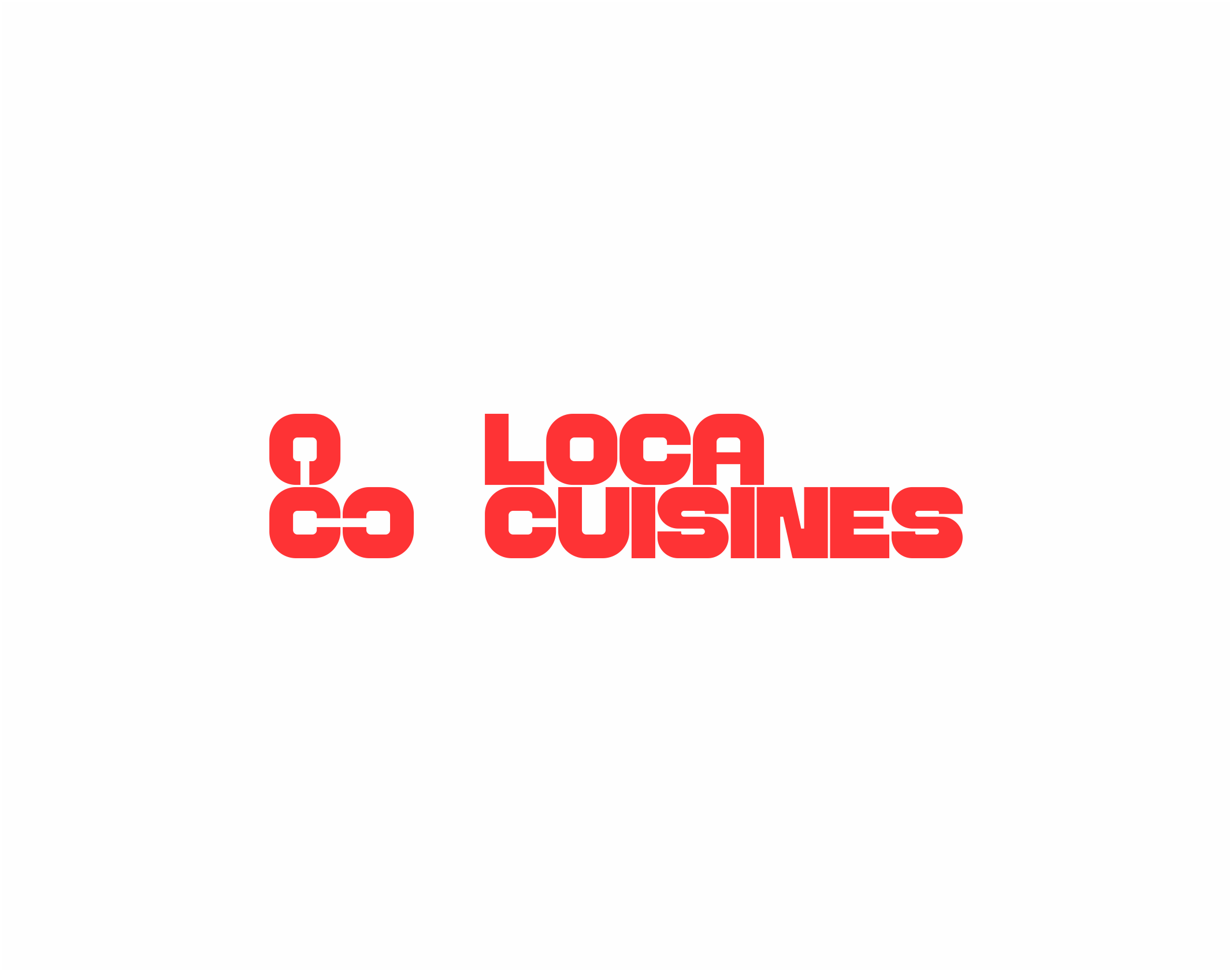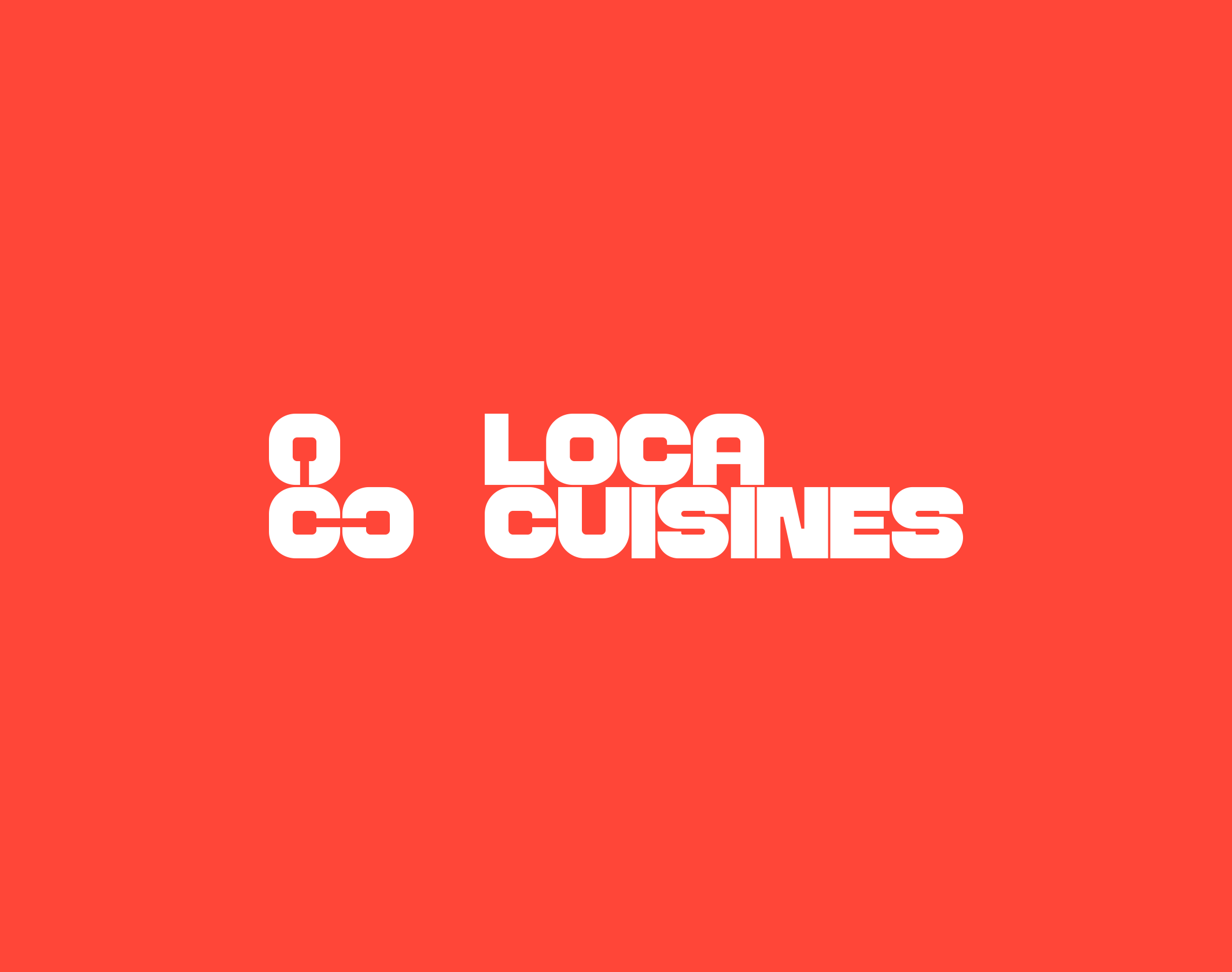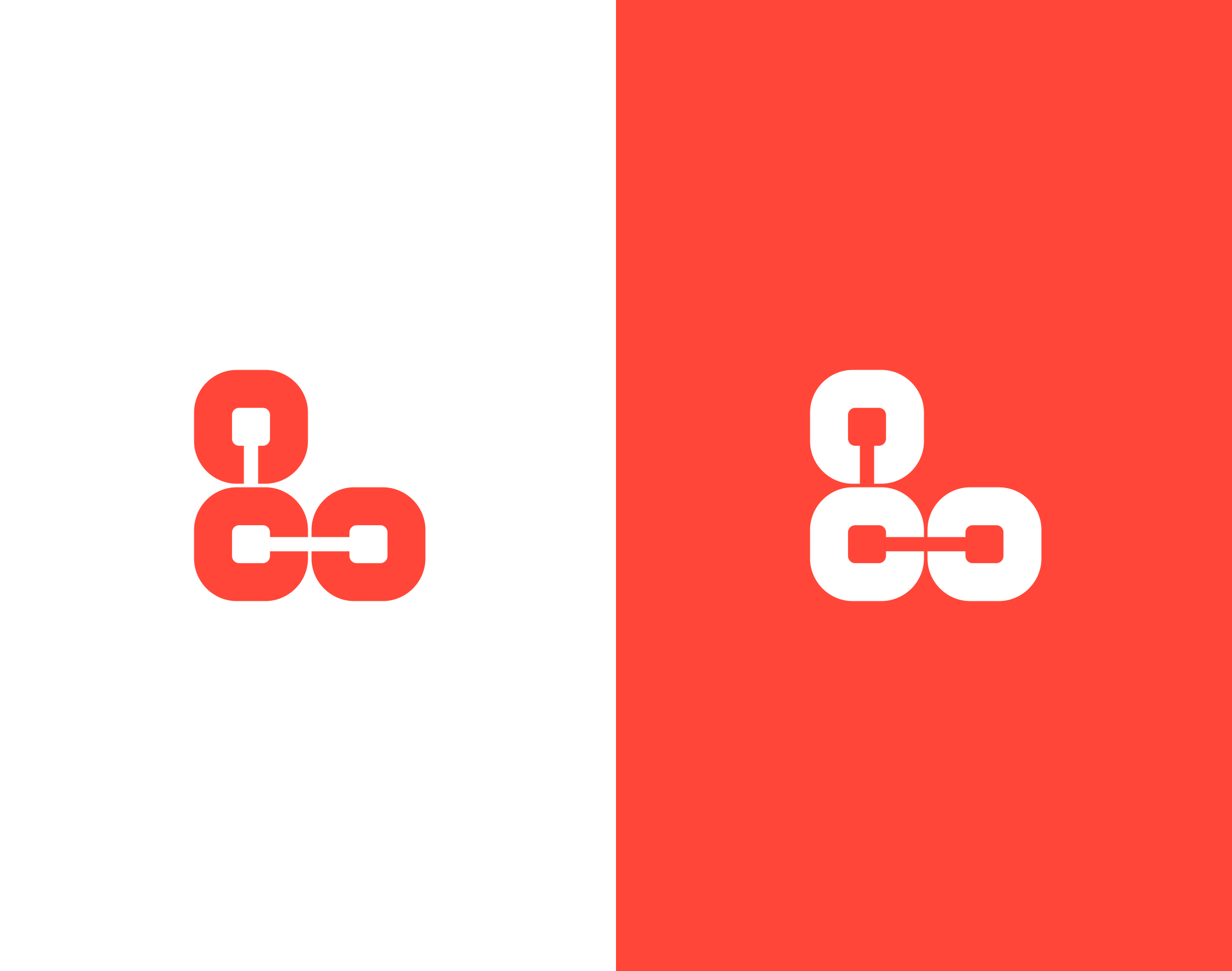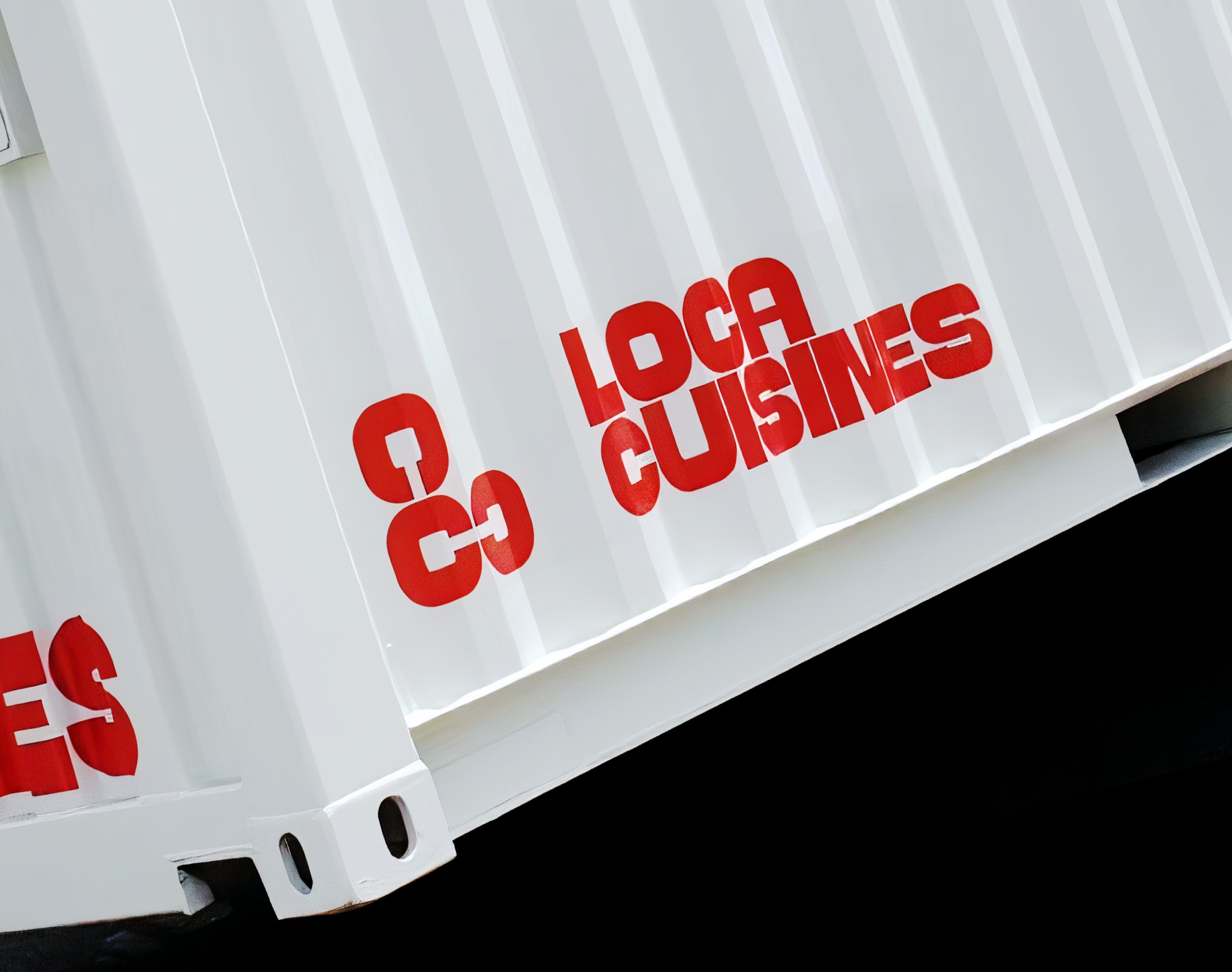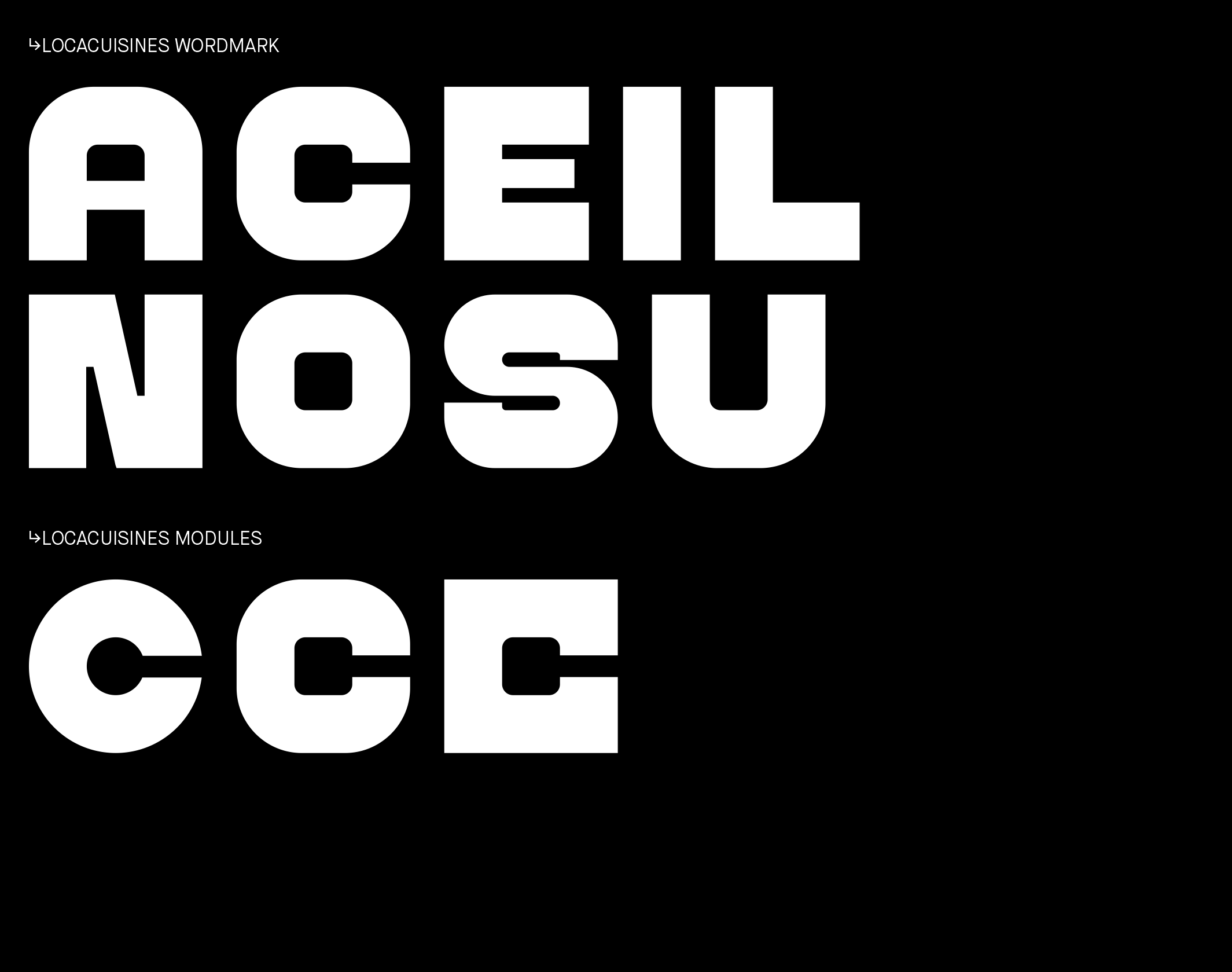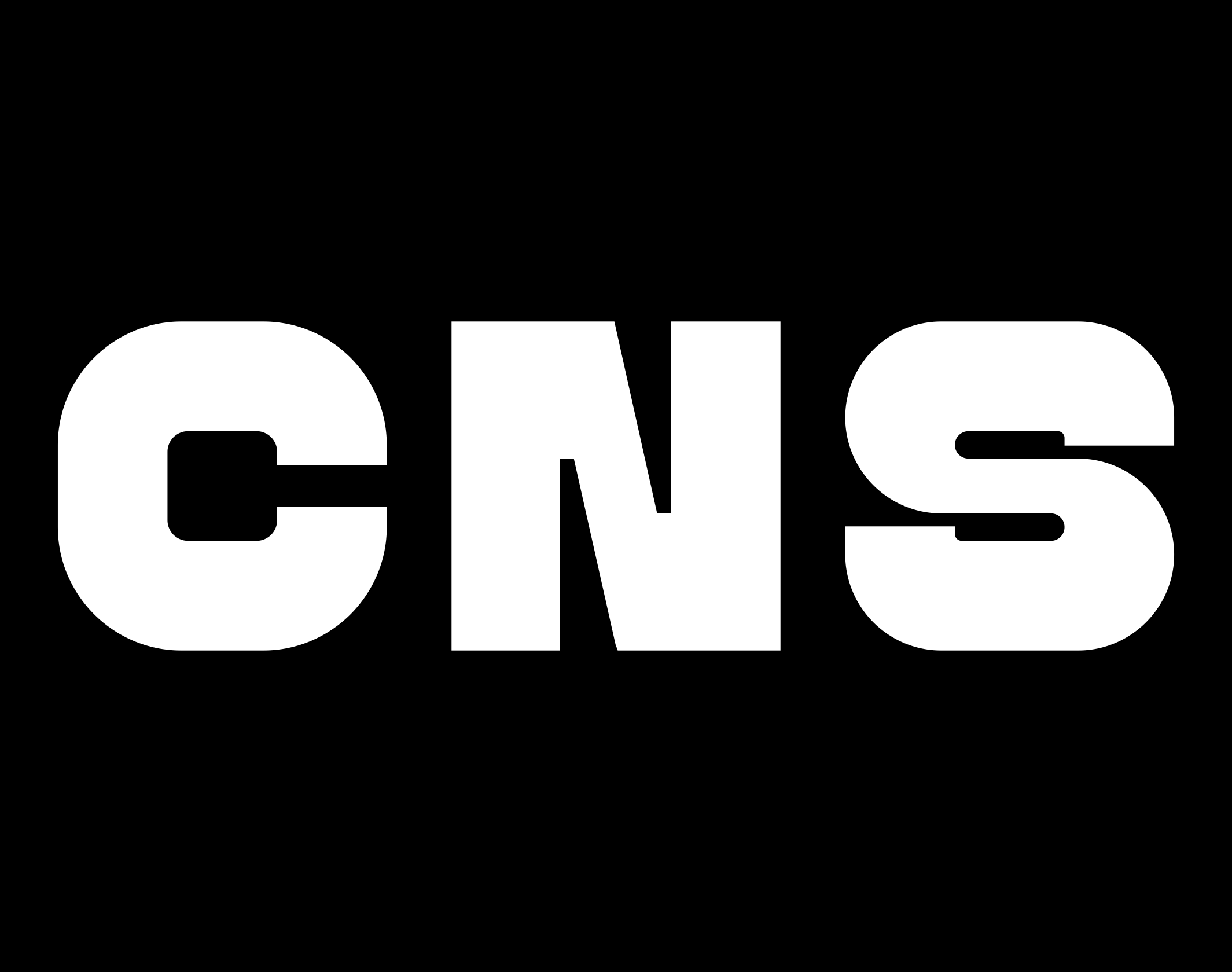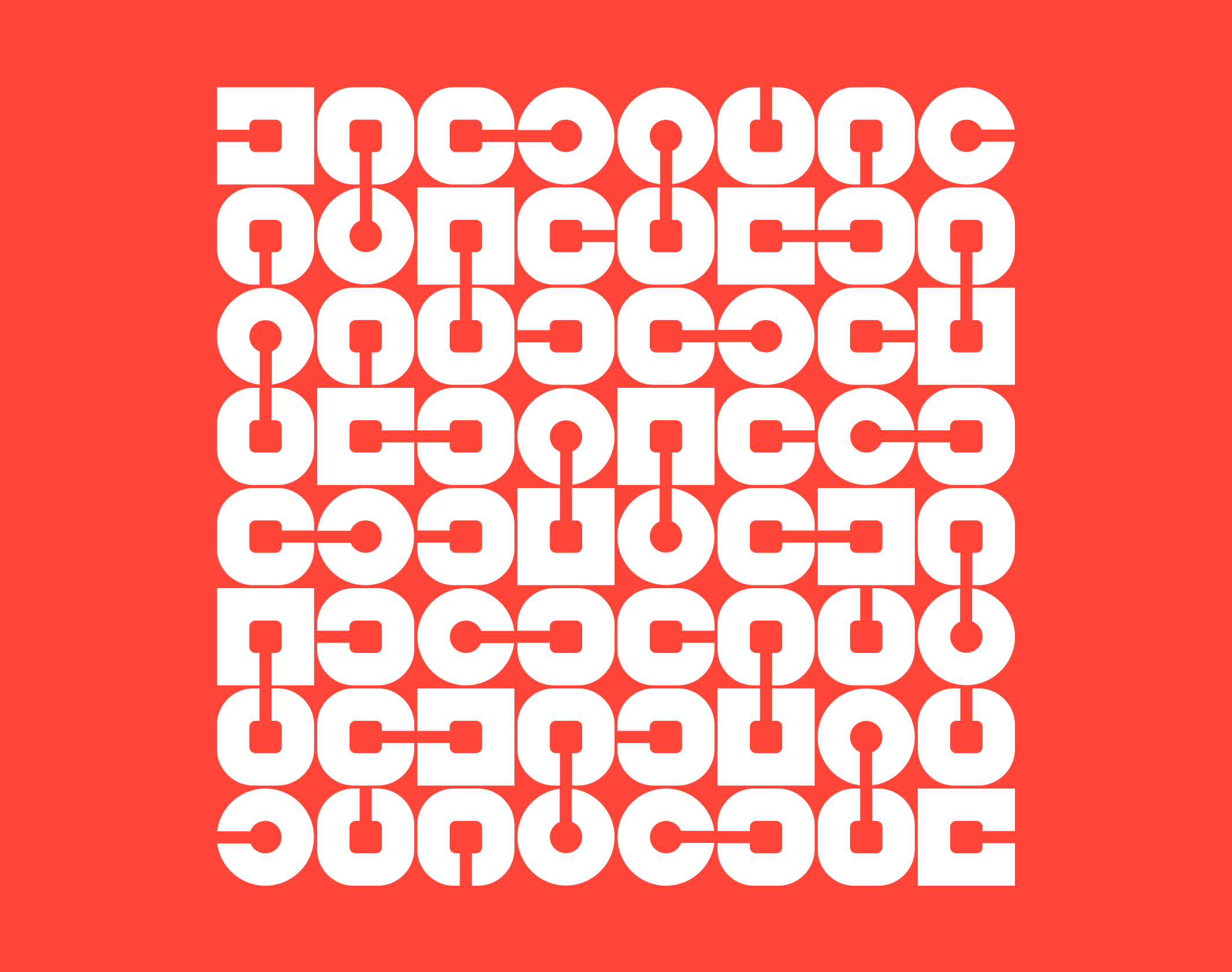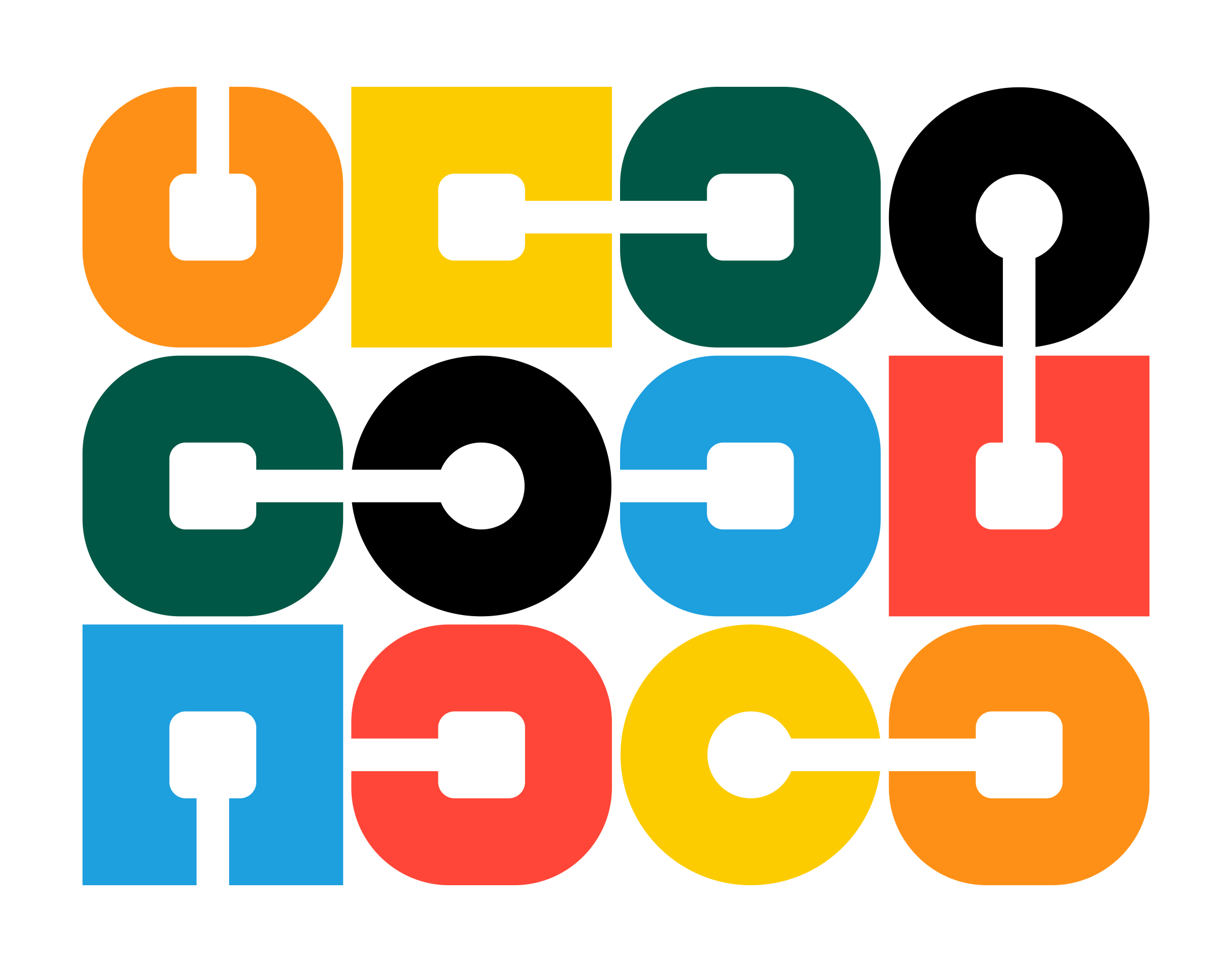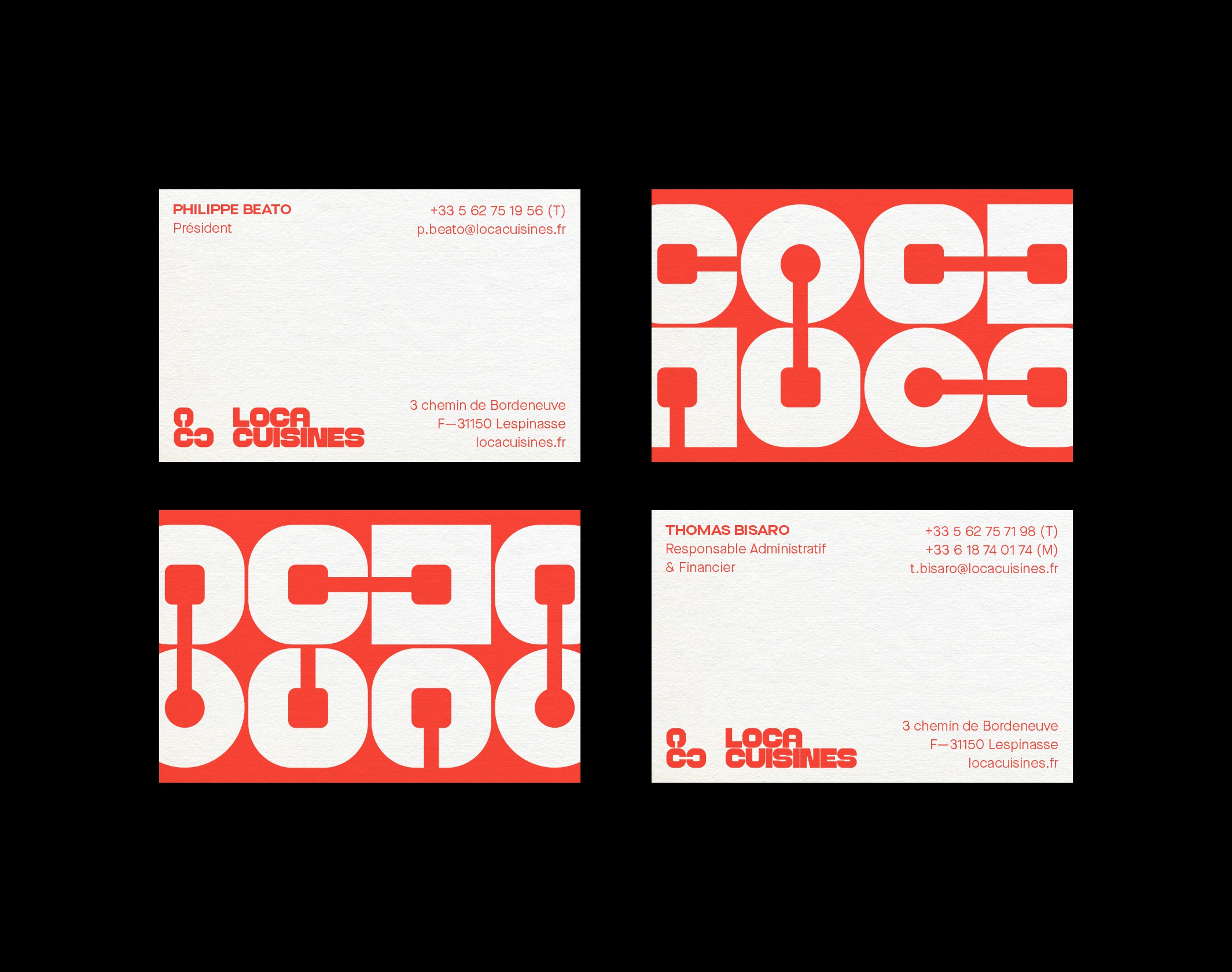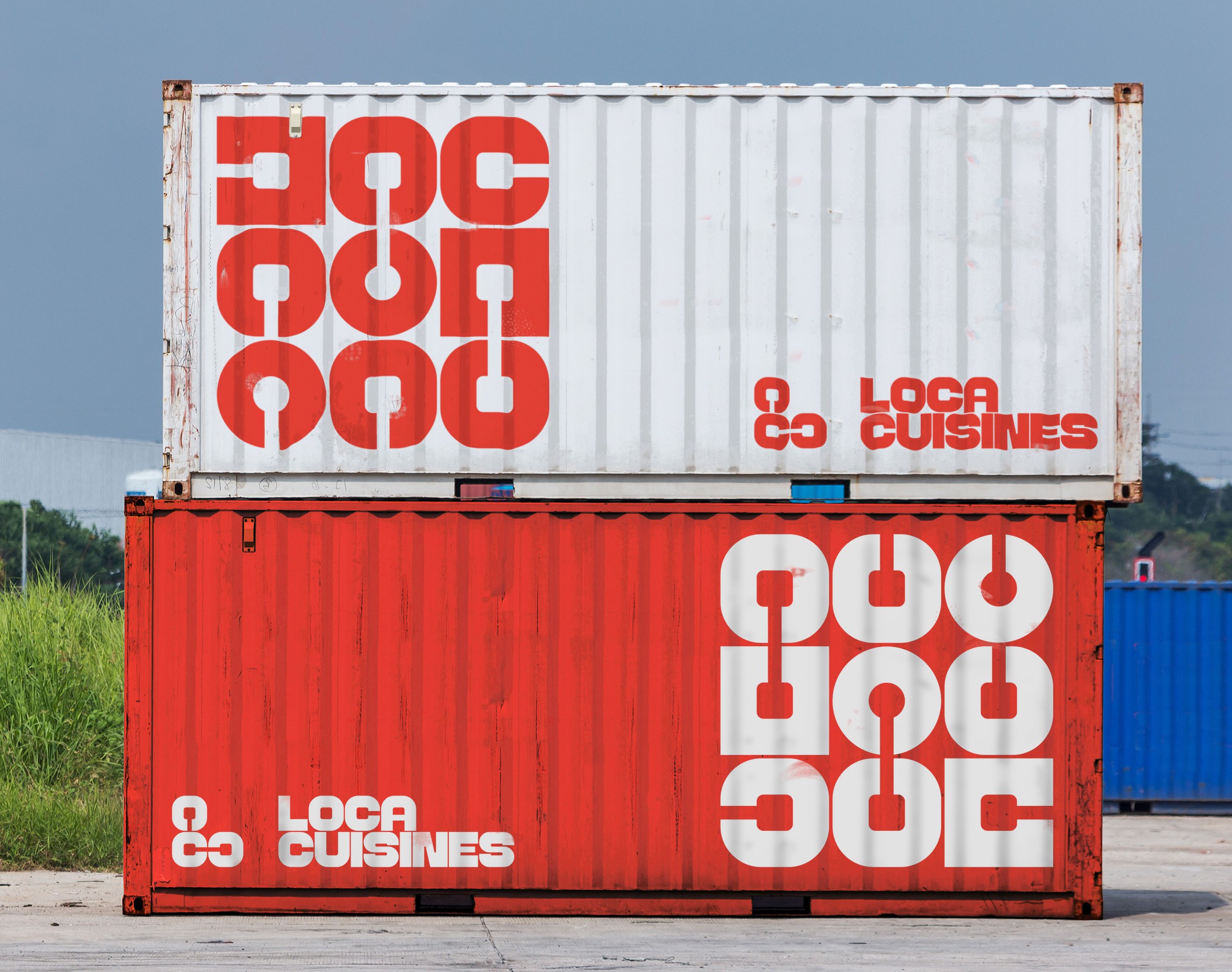
Locacuisines
Locacuisines a transformé son identité visuelle avec un système modulaire, illustrant l'assemblage créatif d'espaces de restauration éphémères.
Locacuisines est le leader français des espaces de restaurations ephémères depuis 1996. Basée en périphérie de Toulouse, cette société a conçu et industrialisé des structures modulaires qui permettent en un temps record de monter des cuisines provisoires, pour 50, 1000 ou 10 000 repas, voire davantage. Présent sur tout le territoire, Locacuisines a équipé des zones de bureaux, des sites en construction, des écoles, groupes hospitaliers, mais aussi le site d’assemblage du Rafale, la Maison des Eaux de Vies à Cognac, Disneyland Paris ou une station de ski des Alpes françaises.
Lorsque Locacuisines a contacté le studio pour repenser son identité visuelle, un système modulaire s’est rapidement imposé. La nouvelle accroche (Assembler pour rassembler) est devenue le point de départ du langage graphique que nous avons développé. Sur la base d’un design typographique maison, le symbole, un L formé de 3 modules C, s’étend pour former un ensemble de modules qui se connectent entre eux à l’envi. Une représentation métaphorique de l’assemblage de modules de restauration, formant des espaces de vie ephémères. Une attention particulière a été apportée au déploiement de ce nouveau système visuel dans un environnement complexe : constructions modulaires, conteneurs maritimes réaménagés, véhicules de livraison, tenues de travail, supports imprimés… le nouveau territoire que nous avons mis en place s’est avéré pratique et simple à mettre en oeuvre, tout en offrant une multitude de possibilités visuelles.